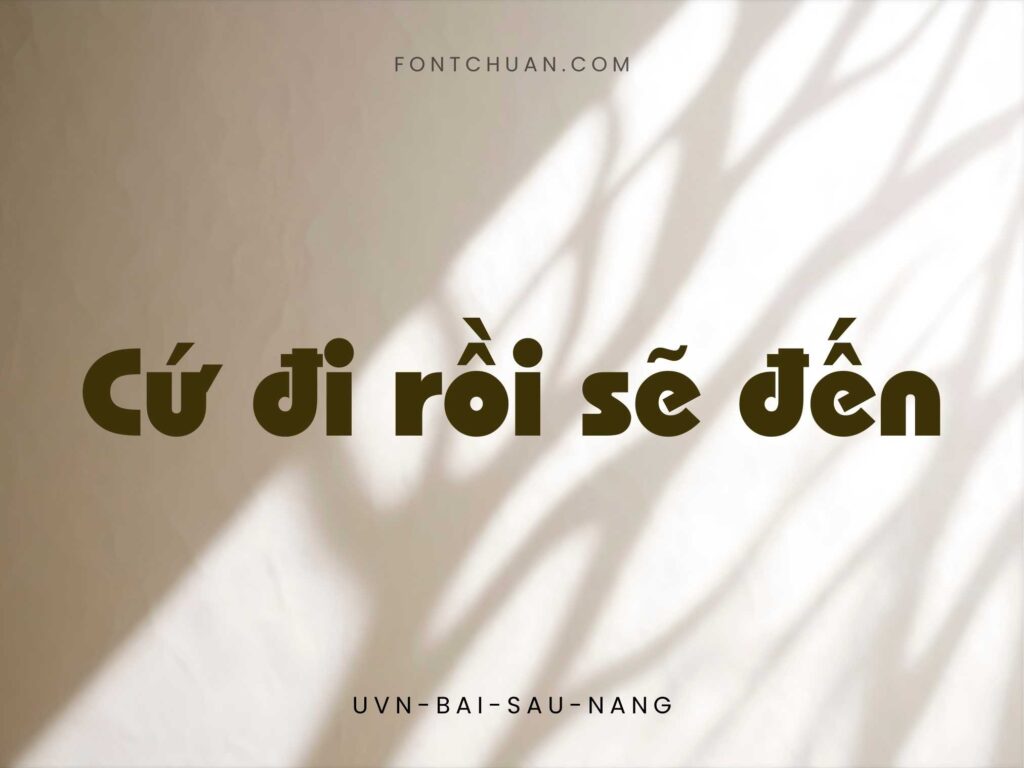
Font UVN Bai Sau Nang Việt Hóa
UVN Bãi Sậu Nặng là một phông chữ sans-serif được thiết kế bởi Tom Trương vào năm 2001. Phông chữ này có kiểu dáng đơn giản, rõ ràng và dễ đọc, phù hợp cho nhiều mục đích sử dụng khác nhau. Với thiết kế gọn gàng và tinh tế, UVN Bãi Sậu Nặng giúp tăng cường tính thẩm mỹ và chuyên nghiệp cho các dự án thiết kế. Phông chữ này đã được Việt hóa, hỗ trợ đầy đủ các ký tự tiếng Việt, giúp người dùng tại Việt Nam dễ dàng sử dụng trong các dự án sáng tạo của mình.
Với thiết kế đơn giản và hiện đại, UVN Bãi Sậu Nặng phù hợp cho các ứng dụng như thiết kế đồ họa, quảng cáo, biên tập văn bản và các ấn phẩm truyền thông. Trong lĩnh vực sự kiện, phông chữ này có thể được sử dụng trong các dịp như lễ hội, hội nghị và các sự kiện văn hóa. Ngoài ra, UVN Bãi Sậu Nặng cũng thích hợp cho các ngành nghề như giáo dục, công nghệ và truyền thông.